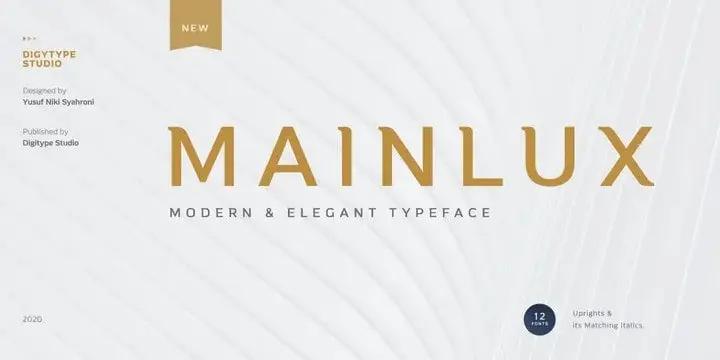
A Mainlux Sans Serif Font é uma tipografia sans serif que destaca-se por sua simplicidade, elegância e versatilidade. Foi projetada para designers que valorizam a leitura fácil e moderna. A fonte mantém a robustez da tipografia de linhas simples, mas com um ar mais leve e menos rígido do que as serifadas. O designer Digitype Studio trouxe uma personalidade única para cada caracter, criando uma família elegante e versátil. Esta font vem em 12 pesos diferentes, incluindo 6 tipos diretos e itálicos, permitindo a criação de designs variados que se adequam perfeitamente ao mundo moderno da design gráfico.